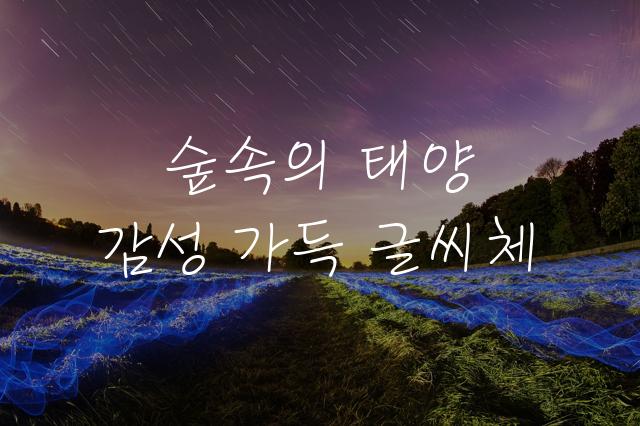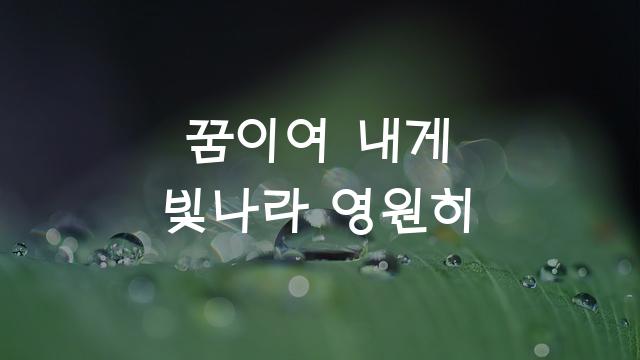
‘태-조각’은 태시스템에서 제작한 기본 고딕 스타일의 폰트로, 제목용으로 적합하며 독특한 디자인이 특징입니다. 감성과 기능을 겸비한 이 폰트는 모던하면서도 강렬한 인상을 줍니다.
태-조각은(는)
기본 고딕, 감성적인, 부드러움, 길고/크고 계열의 생김새를 가지고 있으며
포스터, 초대장, 출판물 제목 등에서 자주 활용되며, 효과적인 메시지 전달에 적합합니다.
이 폰트는 출판/미디어, 문화/예술, 이벤트/웨딩 분야에 잘 어울리며,
강렬한, 예술적인, 클래식한 느낌을 담고 있는 것이 특징입니다.